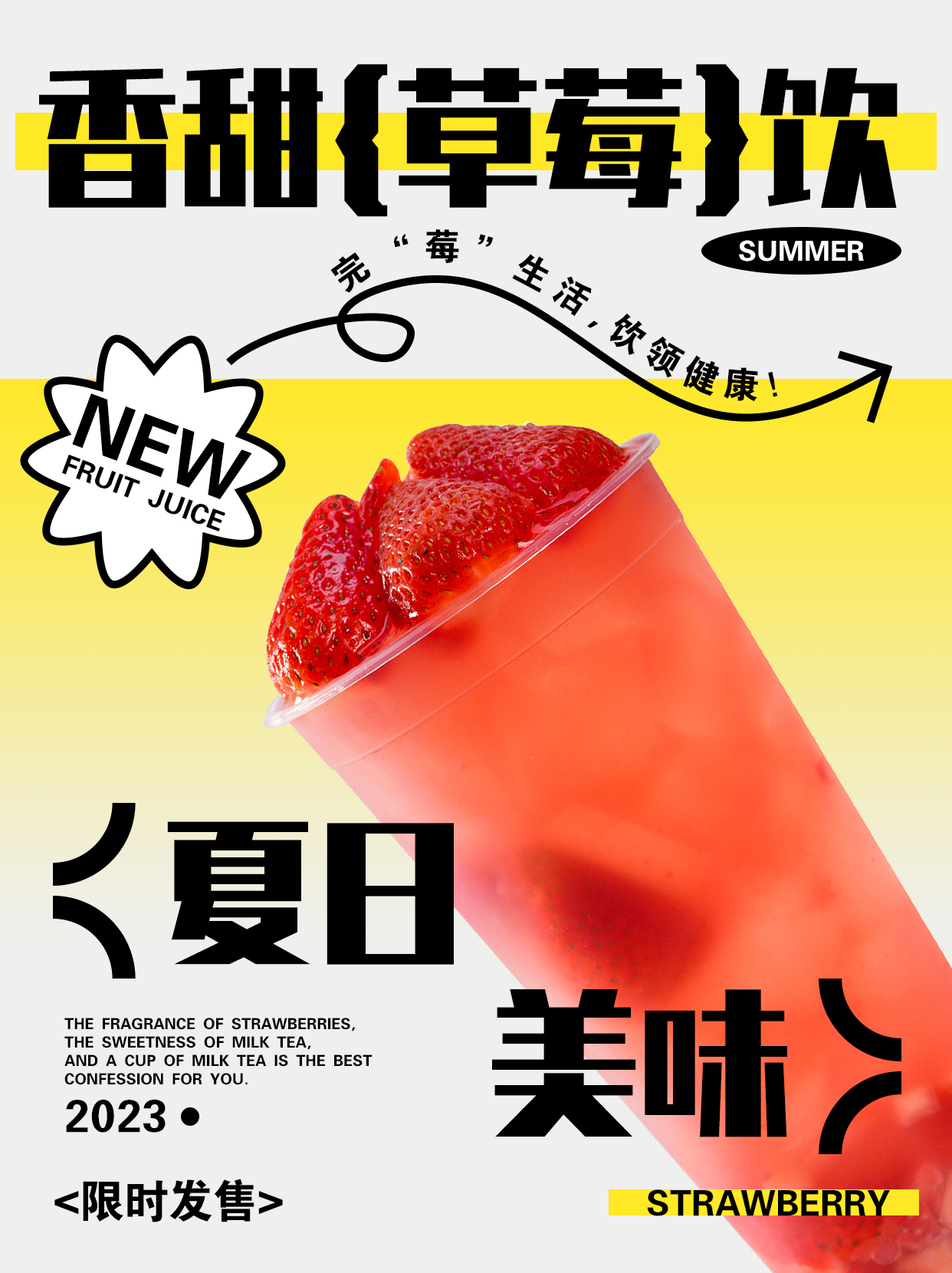
锐字工房金刚黑简1.0 大黑
REEJI-JinGangGB1.0 ExtraBold
原锐字工房金刚黑简1.0 大黑现已更新升级为锐字潮牌金刚黑简2.0 超黑
锐字工房金刚黑简1.0 大黑
黑体
超大黑(ExtraBold)
锐字工房金刚黑是一款粗犷黑色风格的标题字,通过简单大气笔画,给人非常沉稳醒目的感觉,适合报刊、广告等标题设计。